Bộ Font Full
Bộ Font Full sẽ cung cấp cho các bạn tất cả những font chữ tiếng Việt phổ biến nhất hiện nay. Hãy tải Bộ Font đầy đủ này về để thoải mái gõ tiếng Việt có dấu nhé.
Tổng quan
Bộ Font Full sẽ cung cấp cho các bạn tất cả những font chữ tiếng Việt phổ biến nhất hiện nay. Hãy tải Bộ Font đầy đủ này về để thoải mái gõ tiếng Việt có dấu nhé.
Bộ Font Full sẽ cung cấp cho các bạn tất cả những font chữ tiếng Việt phổ biến nhất hiện nay. Với bộ Bộ Font Full người dùng có thể thoải mái lựa chọn font chữ để soạn thảo văn bản, thiết kế, chat, vv theo cách chuẩn mực nhưng cũng đầy sáng tạo. Thay vì những font chữ quá đơn giản bạn hãy sử dụng bộ font chữ này của chúng tôi để có thêm nhiều cảm hứng khi làm việc.
Nếu máy tính của bạn thường xuyên gặp các lỗi liên quan đến thiếu font chữ thì Bộ Font Full chính là lựa hoàn hảo. Mỗi font chữ trong Bộ Font Full đều có những đặc trưng rất riêng, không chỉ là các font chữ cơ bản mà rất nhiều font chữ nghệ thuật dành riêng cho dân thiết kế thỏa sức sáng tạo cho bản vẽ của mình.
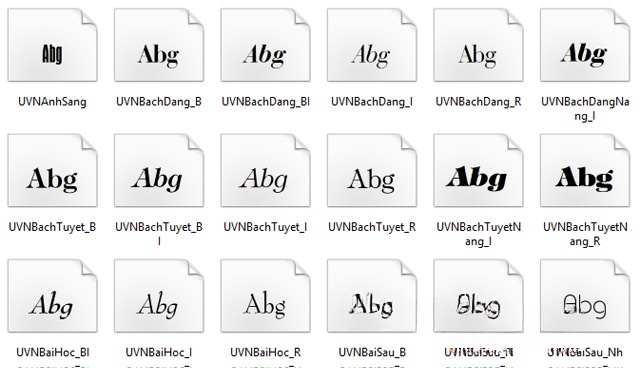
Bộ Font Full gồm trọn bộ font Unicode, font TCVN3, font VNI và font UTM.
Bộ sưu tập Font full mang tới cho người dùng đầy đủ các loại font thuộc nhiều bảng mã khác nhau như .VNI, Vntime ... Mỗi loại font đều có thiết kế về kiểu dáng khác nhau, phù hợp với nhiều đối tượng sử dụng cũng nhiều yêu cầu của người dùng. Những người thiết kế thường sử dụng những loại font có nét chữ uốn lượn như font thư pháp, còn những người soạn thảo văn bản thường dùng font Time New Roman hay Arial ...
Tính năng chính của Font full
Khắc phục lỗi và Hỗ trợ hiển thị đầy đủ:
- Hỗ trợ tiếng Việt đầy đủ: Đây là tính năng quan trọng nhất. Bộ font full bao gồm font thuộc nhiều bảng mã phổ biến như Unicode, TCVN3, VNI, UTM, giúp bạn gõ và xem văn bản tiếng Việt có dấu một cách chính xác trên mọi phần mềm, ứng dụng mà không bị lỗi (hiển thị ký tự lạ, ô vuông).
- Bao gồm đầy đủ ký tự: Hỗ trợ mọi ký tự cần thiết bao gồm: chữ thường, chữ hoa, số, dấu câu, ký tự đặc biệt và các dấu tiếng Việt.
- Đảm bảo tính ổn định tài liệu: Khi trao đổi hoặc mở file văn bản ( Word, PowerPoint, PDF) từ người khác, việc có bộ font đầy đủ sẽ giúp tài liệu hiển thị đúng định dạng gốc, tránh bị biến dạng hay thiếu font.
Đa dạng và Linh hoạt trong sử dụng:
- Bộ sưu tập font phong phú: Cung cấp hàng trăm kiểu font khác nhau, từ font phổ thông, chính thức (Unicode) đến các font nghệ thuật, sáng tạo như font thư pháp, font nét bút, đáp ứng đa dạng nhu cầu của người dùng, đặc biệt là dân thiết kế đồ họa.
- Nhiều biến thể (Style): Mỗi font thường đi kèm với các kiểu như Regular, Bold, Italic, Light, Semi-Bold, giúp bạn linh hoạt tùy chỉnh độ đậm, nghiêng, tạo điểm nhấn và sự tương phản cho tiêu đề và nội dung văn bản.
- Tạo tính chuyên nghiệp và cá nhân hóa: Sự đa dạng về kiểu dáng giúp người dùng tạo ra các sản phẩm thiết kế, quảng cáo, bài thuyết trình mang tính thẩm mỹ cao, chuyên nghiệp và thể hiện được cá tính riêng.
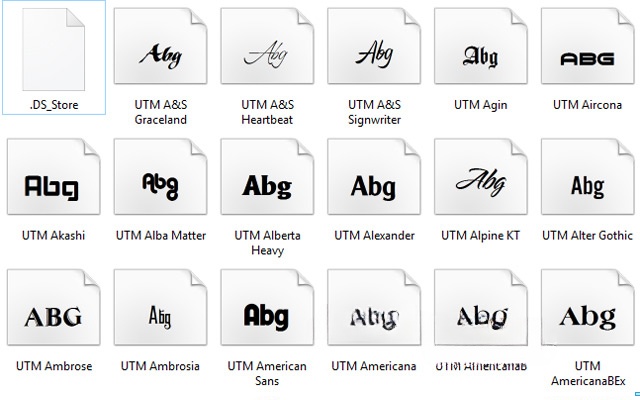
Bộ font UTM với nhiều kiểu chữ khác nhau cho bạn thoải mái lựa chọn.
Tính tương thích và Chất lượng:
Chất lượng đường nét tốt: Các ký tự (glyph) được thiết kế rõ nét, đẹp mắt ngay cả khi bạn phóng to hoặc thu nhỏ, đảm bảo chất lượng hiển thị trên màn hình lẫn khi in ấn.
Tiết kiệm thời gian: Thay vì phải tìm kiếm và cài đặt từng font lẻ từ nhiều nguồn, việc cài đặt bộ font full giúp bạn có sẵn một kho font phong phú chỉ trong một lần tải về.